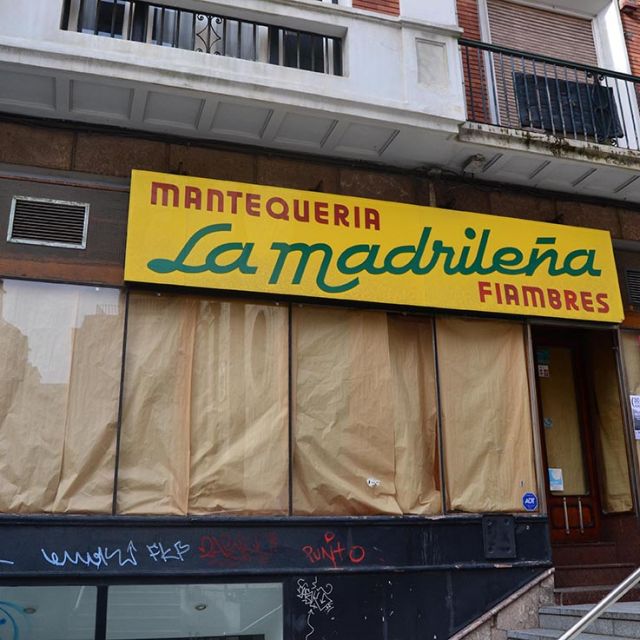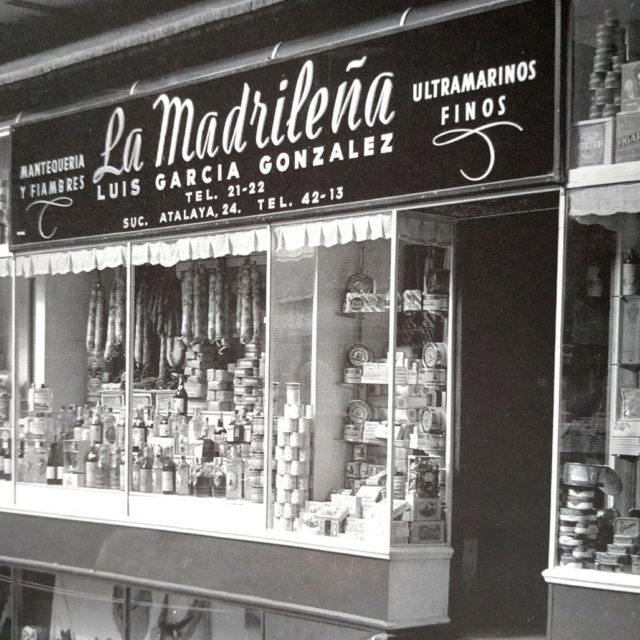
Mantequerias La Madrileña
La vorágine del día a día hace que en las calles se abran y cierren tiendas. No por ello, quita que con el tiempo la ciudad vaya perdiendo esa identidad particular en sus calles. En el blog procuraremos recordar esos viejos rótulos que de algún modo han formado parte de la Historia de Santander, como son el caso de la «Marmolería» en la calle Gravina y «Tejidos Antonio» en la calle San Francisco.
Mantequerías La Madrileña quizás fue uno de los primeros negocios de productos gourmet y delicatessen que se instalaron en Santander. Fue abierta en 1952 y regentada totalmente por la propia familia.Aún en 2006 era objeto de referencia, con motivo de las navidades. Su característico rótulo amarillo, con su particular script, aún se podía ver hasta finales de 2014 en las escaleras de la calle Santa Clara, junto a la Parroquia de la Anunciación.
A finales de 2014 se comenzó la obra del local y el rótulo desapareció.
Rótulo original de vidrio, probablemente realizado por el Taller de Noval | Fuente: «Vamos de Tiendas», Memoria gráfica del comercio de Santander. Santander, 2015
Noviembre de 2014. Foto: Santatipo
Hoy. Foto: Santatipo
Logo antiguo| Fuente: Asociación Comerciantes Casco Viejo de Santander
Interior| Fuente: Asociación Comerciantes Casco Viejo de Santander